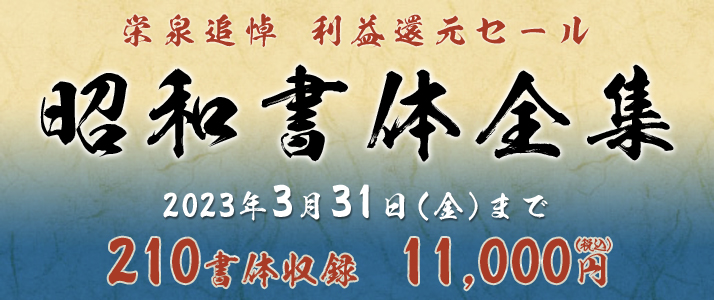
一文字一文字、丁寧に書き上げた直筆の筆文字をフォントとして制作・販売する昭和書体。
その多くの書体を手掛けてきた綱紀栄泉氏の今年3月のご逝去を受け、
故人の遺言ともなった「もっと安くして、全国で私の文字を1人でも多くの方々に使ってほしい」
との思いを実現するためにキャンペーンを実施することとなりました。
全210書体(和文フォント92書体、欧文フォント114書体、梵字フォント4書体)を収録。